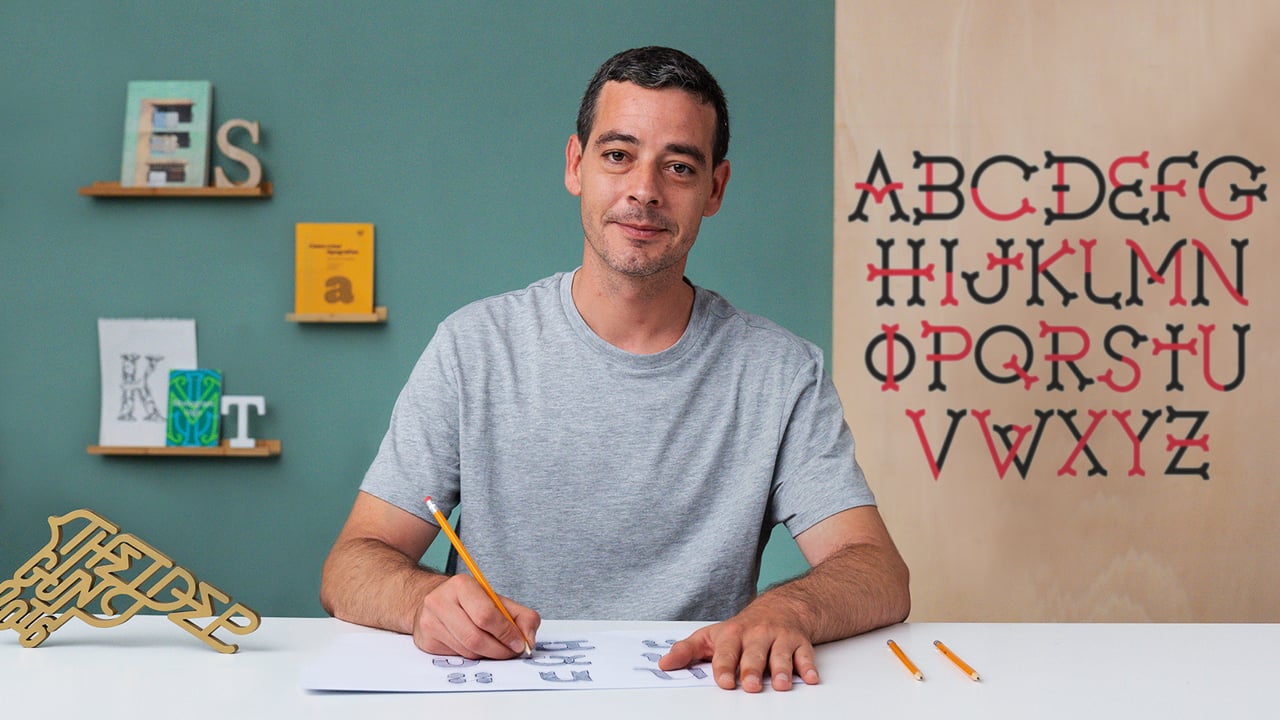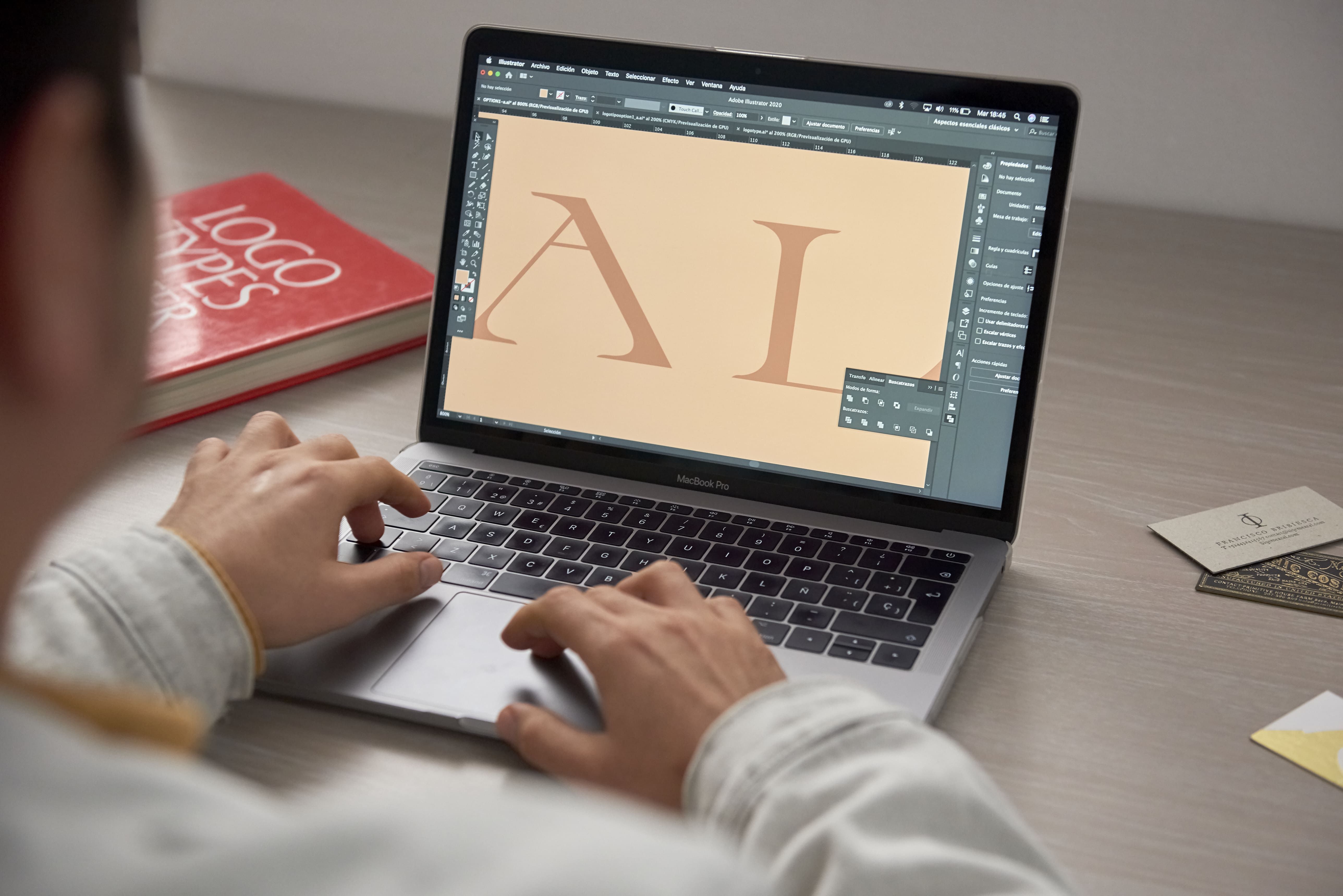
10 cursos online de tipografía para diseñadores gráficos en 2025
Crea tus propias fuentes tipográficas en Glyphs, Illustrator o After Effects con estos cursos esenciales de diseño gráfico
Comunicar una idea de forma estética y comprensible es la principal misión de la tipografía, una rama del diseño gráfico con la que interactuamos diariamente pero en la que solemos reparar poco.
Así, pensando en honrar esta disciplina tan presente en nuestras vidas, hemos seleccionado 10 cursos online de tipografía imprescindibles para todos los diseñadores gráficos sin importar su área de especialización. Descubre cómo crear una familia de letras o tipografías para logotipos, en Glyphs, Adobe Illustrator o After Effects y diseña composiciones estáticas o dinámicas increíbles.
Principios básicos del diseño tipográfico, un curso de Latinotype
Daniel Hernández y Luciano Vergara son los nombres detrás de Latinotype, el primer despacho chileno dedicado enteramente a crear tipografías para fines comerciales. Entre sus clientes más destacados se encuentran Starbucks, Converse y Movistar, por mencionar algunos.
En su curso, Principios básicos del diseño tipográfico, aprenderás cuáles son los elementos fundamentales que toda familia de letras debe tener: desde el ritmo y la forma hasta la coherencia visual y el espacio entre caracteres. Al finalizar las lecciones, serás capaz de crear tu propio alfabeto con 26 minúsculas y mayúsculas.
Personalización de tipografías para diseño de logotipos, un curso de Monotypo Studio
Aunque casi siempre usamos la palabra “logotipo” para hablar de cualquier símbolo gráfico que identifique a una marca, en realidad este término únicamente es válido para los que emplean letras en su composición. Conocer la diferencia es de suma importancia para los diseñadores gráficos, pues al crear un logotipo deberán encapsular la esencia de la marca recurriendo solo a la tipografía.
Para ayudarte a lograrlo cuentas con la guía de Daniel Barba López, director de Monotypo Studio, quien en su curso Personalización de tipografías para diseño de logotipos te enseña a modificar tipografías ya existentes para crear con ellas logotipos completamente inéditos.
Creación de tu propia tipografía, un curso de Wete
Diseñar tus propias fuentes tipográficas es siempre una buena idea, ya sea que desees darle un toque más personal a tu proyecto o incluso te interese venderlas a tus clientes o en webs especializadas.
Comprueba lo divertido que puede ser convertirse en tipógrafo con Wete, quien imparte el curso Creación de tu propia tipografía. En él repasarás los conceptos básicos de la tipografía, para después dibujar una familia de letras usando lápiz, papel y las herramientas de Adobe Illustrator. Al finalizar el curso tendrás tu propia tipografía trazada en Glyphs, el software que usan los profesionales.
Adobe Illustrator para tipografía, lettering y caligrafía
Si tuviéramos que describir Adobe Illustrator con una sola palabra esta sería “versatilidad”, pues con este poderoso programa de trazo vectorial puedes incluso diseñar tu propia familia de letras.
Te lo va a demostrar Andrés Ochoa en su curso, titulado Adobe Illustrator para tipografía, lettering y caligrafía. Pensado para los diseñadores gráficos que inician, está dividido en cinco cursos básicos, en los que aprenderás a dominar el software y a trazar las formas básicas que se convertirán en letras. También te enseñará a aprovechar las fuentes ya precargadas.
Introducción a Glyphs, un curso de Wete
¿Recuerdas que más arriba te dijimos que Glyphs es uno de los programas más usados por los tipógrafos profesionales? Si estás incursionando en el diseño gráfico, y quieres saber los motivos, el curso Introducción a Glyphs te interesa.
Empezarás familiarizándote con la interfaz de usuario y conociendo las ventajas de usar este software, para luego establecer los puntos básicos de tu fuente tipográfica y exportarla. Lo mejor es que tendrás como profesor a Wete, reconocido tipógrafo que ha trabajo con Adobe, Reebok y Desigual, entre otras compañías.
Conceptos de la tipografía para pantallas, un curso de Gemma Busquets
Hasta hace unos años, la tipografía era empleada principalmente en impresos. Sin embargo, hoy en día predomina su uso en medios digitales, ¡y las líneas de este blog son buena prueba de ello!
Para que todos tus proyectos de diseño digital sean legibles y se puedan desplegar correctamente en cualquier dispositivo, te sugerimos tomar el curso Conceptos de tipografía para pantallas, de Gemma Busquets. Con más de 10 años de experiencia trabajando con empresas como The Huffington Post y Coca-Cola, ella te dará valiosos consejos en cuanto al diseño de blogs, páginas web, e books y porfolios.
Tipografía para diseñadores: fuentes para marketplaces, un curso de Thomas Jockin
Si te dedicas al diseño gráfico, seguramente más de una vez has tenido que acudir a una web especializada para comprar una tipografía y aplicarla a tu proyecto. Pero, ¿alguna vez te has preguntado quiénes diseñan esas fuentes y qué beneficios económicos perciben?